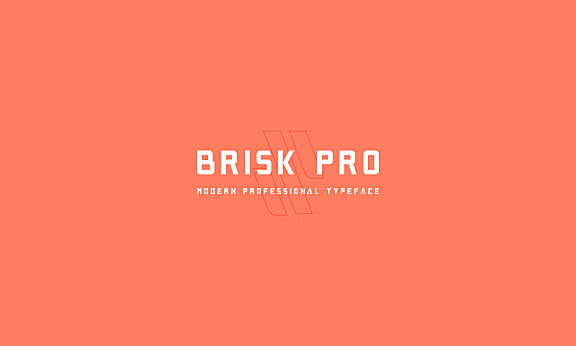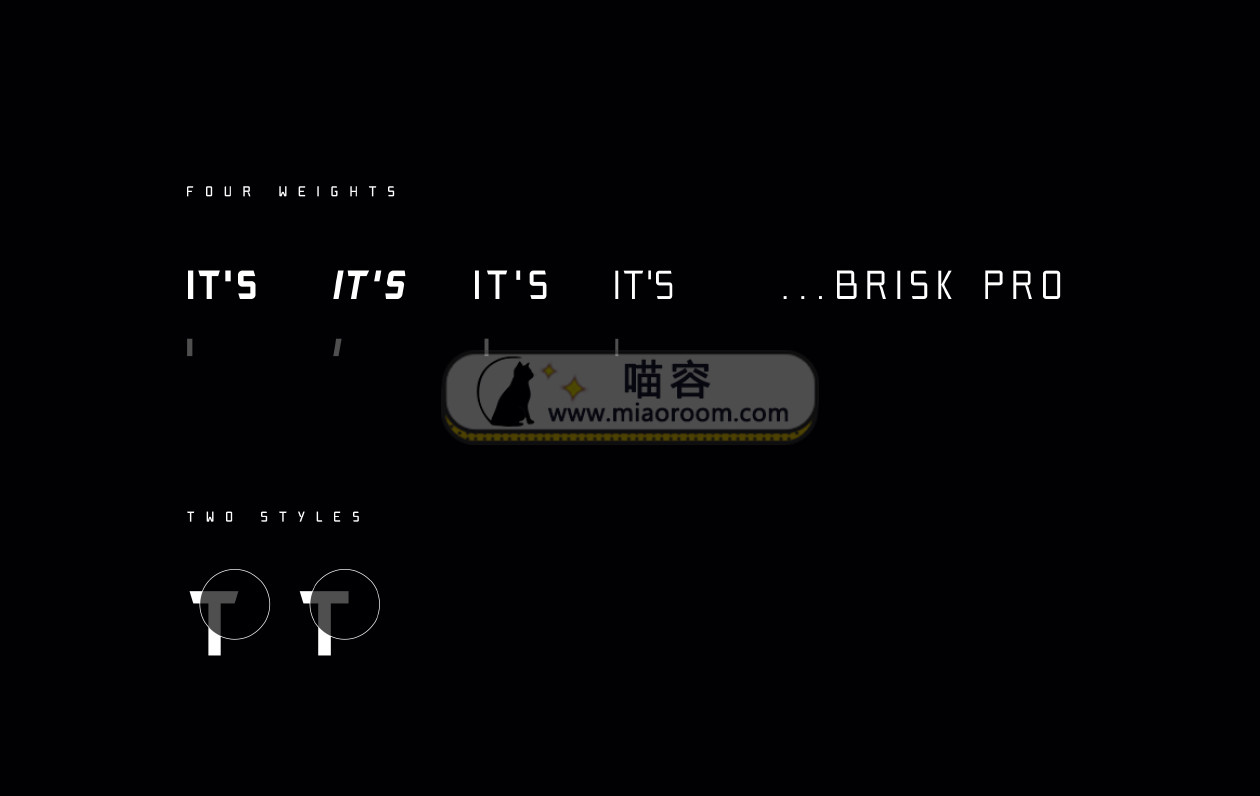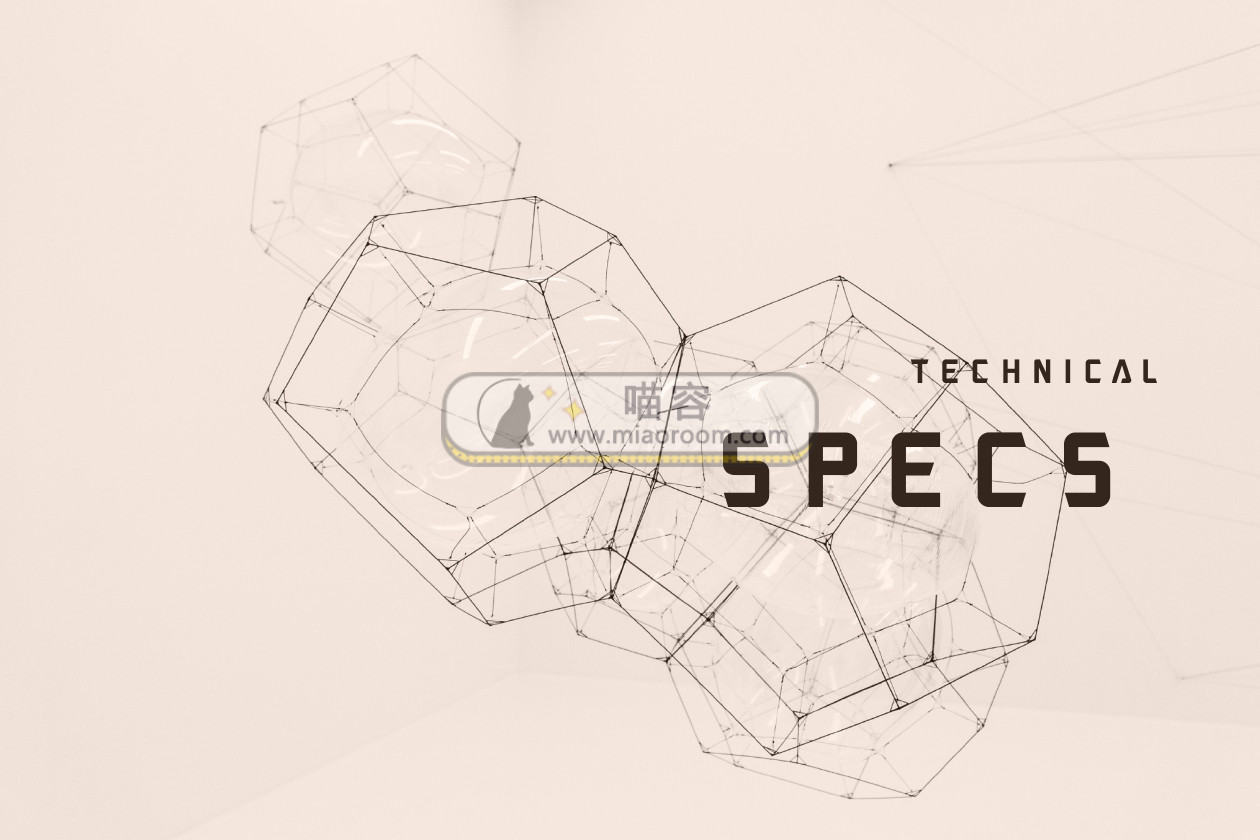
[系统字体] 具有特殊边缘的无衬线字体 资源介绍参数 资源类别: 精美字体 如遇问题: 联系客服/留言反馈 下载地址: 前往下载 精美字体 21年1月19日 编辑 前往下载 喵容发布2号 取消关注 关注 私信 今天分享的是字体叫做Brisk Pro,它具有非常特殊的边缘特征,在海报制作或者logo设计中非常实用。需要的朋友可以到文末下载哦! 相关文章: [系统字体] 复古脚本字体:本文介绍的是一款具有复古外观的脚本字体——Buffalo。它是品牌和标志设计的理想选择,有需要的朋友可以到文末下载哦! 下载权限查看 ¥ 免费下载 评论并刷新后下载 登录后下载 查看演示 {{attr.name}}: 您 …... [系统字体] 一款灵感来自动物的字体:本文分享的一款字体(faune)。这款字体是由Alice Savoie在国家艺术中心与Groupe Imprimerie Nationale合作委托的背景下创建的的。该字体灵感来源于动物,并以两部伟大的历史作品为基础。可以说是一款具有 …... [系统字体] 刷子风格手写字体 MONA字体:资源名称 MONA 资源大小 154kb 资源格式 ttf、jpg 资源简介 Mona是一款手绘笔刷字体,具有对比鲜明的线条。非常适合徽标,海报和包装设计。 喵容——MONA字体1喵容——MONA字体2 下载权限查看 ¥ 免费下载 评论 …... [系统字体] 分层复古字体 BERG字体:资源名称 BERG 资源大小 244mb 资源格式 ttf、png 资源简介 Berg包含一整套大写和小写字母,以及多语言支持,货币数字,数字和标点符号。 喵容——BEGR字体1喵容——BEGR字体2 下载权限查看 ¥ 免费下载 评论并 …... [系统字体]优雅现代手写英文字体 Domillion字体:资源名称 Domillion 资源大小 591kb 资源格式 ttf、otf 资源简介 Domillion是海报,签名,标识,报价,专辑封面,名片,产品设计等的完美选择!该字体免费供个人使用! 喵容——Domillion-Brush-Font1喵容——D …... [系统字体]优质的装饰字体——Sabrva:资源描述 字体 资源名称 Sabrva 资源格式 ttf 资源大小 7.35kb 资源简介 Sabrva是完美字体的选择,可在 – 水印,签名,摄影,徽标,名片,报价,专辑封面使用。免费供个人使用! 喵容——Sabrva1喵容—— …... 下载权限查看 ¥ 免费下载 评论并刷新后下载 登录后下载 查看演示 {{attr.name}}: 您当前的等级为 登录后免费下载登录 小黑屋反思中,不准下载! 评论后刷新页面下载评论 支付¥以后下载 请先登录 您今天的下载次数(次)用完了,请明天再来 支付积分以后下载立即支付 支付以后下载立即支付 您当前的用户组不允许下载升级会员 您已获得下载权限 您可以每天下载资源次,今日剩余次 声明:本文为原创作品,版权归作者所有。未经许可,不得转载或用于任何商业用途。如若本站内容侵犯了原著者的合法权益,可联系我们进行处理。 给TA打赏 共{{data.count}}人 人已打赏 Brisk Prologo设计字体下载海报制作